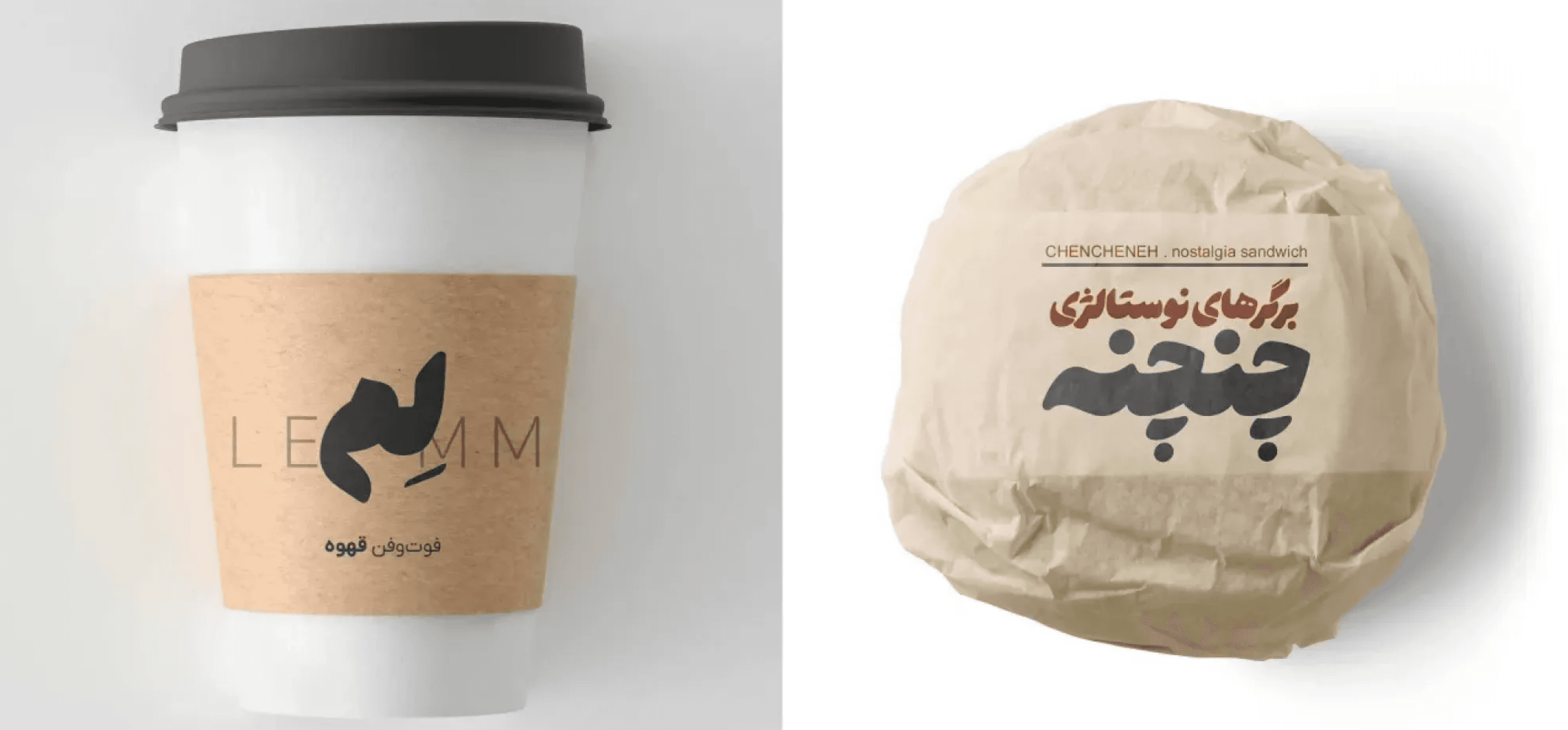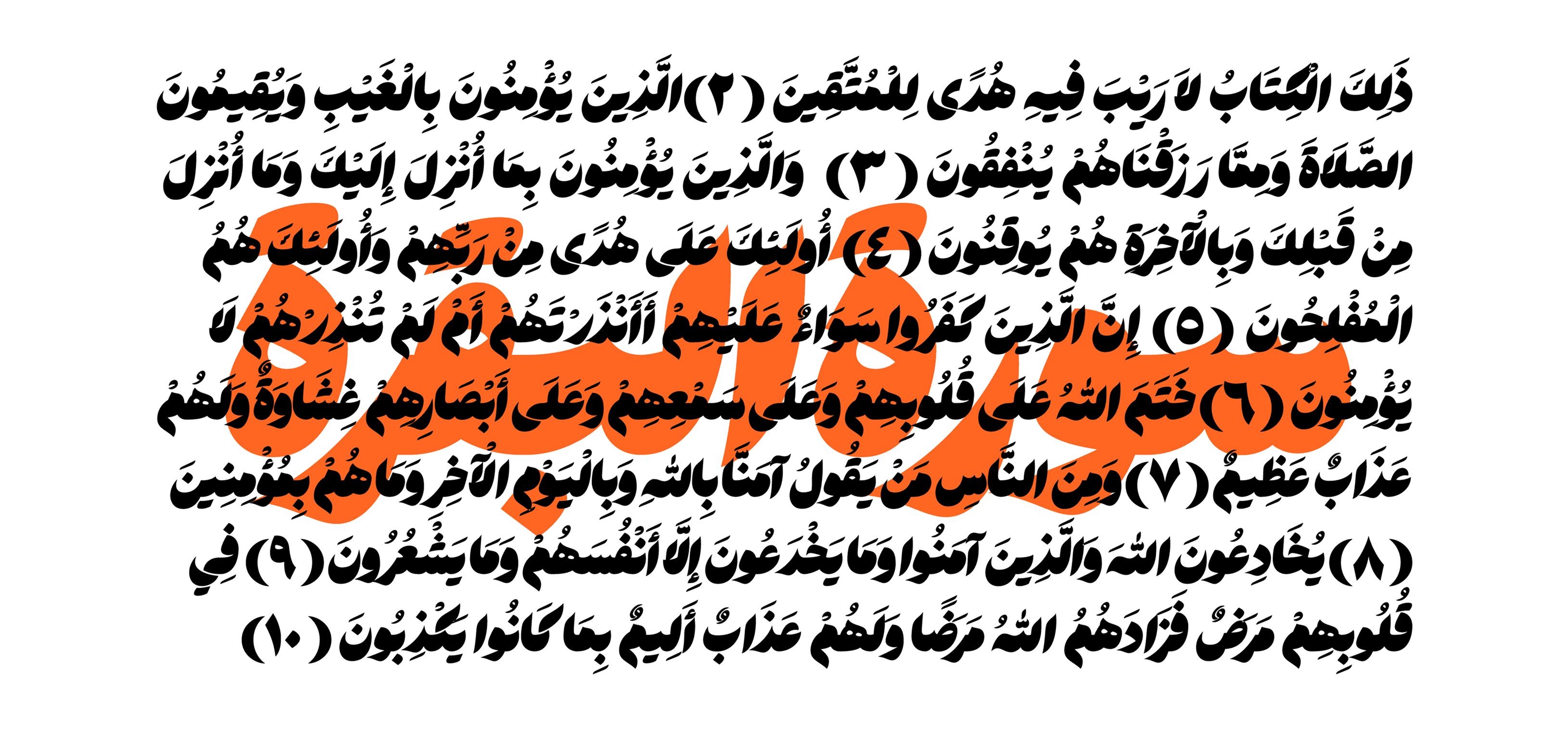
خط Hasti مستوحى من أسلوب النستعليق المستخدم بشكل شائع في اللافتات والإعلانات الخارجية، والذي يُكتب بأقلام خط عريضة ويتميز بكونه أكثر سماكة وتماسكًا من النستعليق التقليدي، لكنه يفتقر إلى جماليته الفنية.
تم تصميم خط Hasti ليكون ضخمًا ومضغوطًا، متأثرًا بهذا النمط من الكتابة، ليتناسب مع الاستخدامات الحديثة التي تتطلب وضوحًا بصريًا عاليًا.